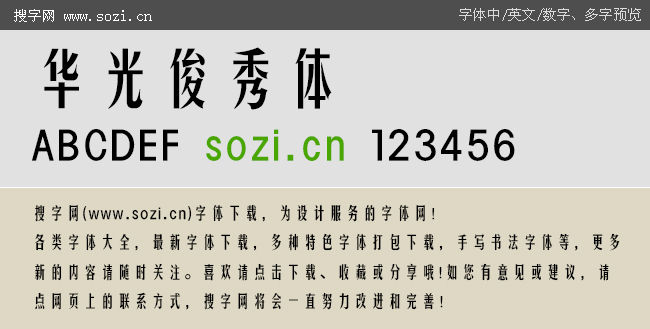
華光俊秀體
搜字網(wǎng)給大家提供一款華光俊秀體中文字體下載,華光俊秀體是一款藝術(shù)姚體字體。這款字體字形挺拔俊美,個性高挑,筆畫剛?cè)岵,字體造型設(shè)計嚴謹并且充滿了美感。適合應(yīng)用于藝術(shù)設(shè)計、平面宣傳設(shè)計、網(wǎng)頁設(shè)計、海報設(shè)計等應(yīng)用。